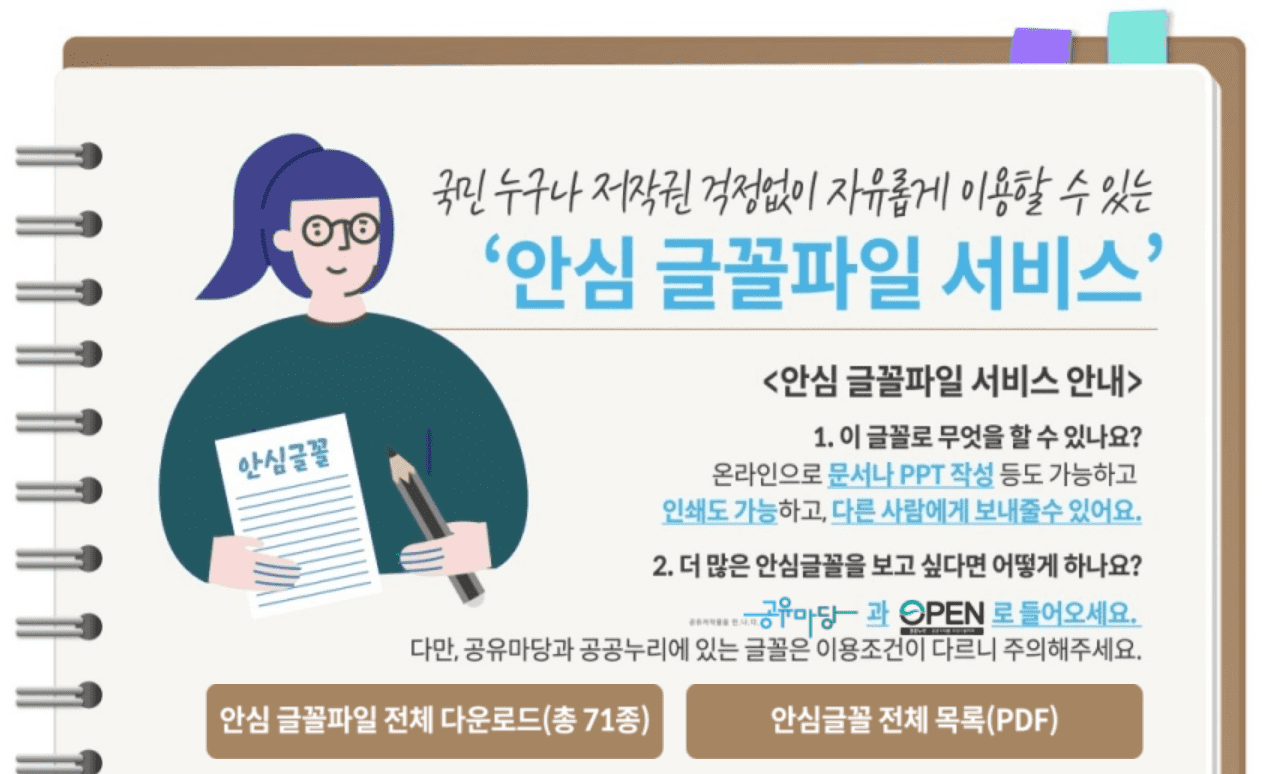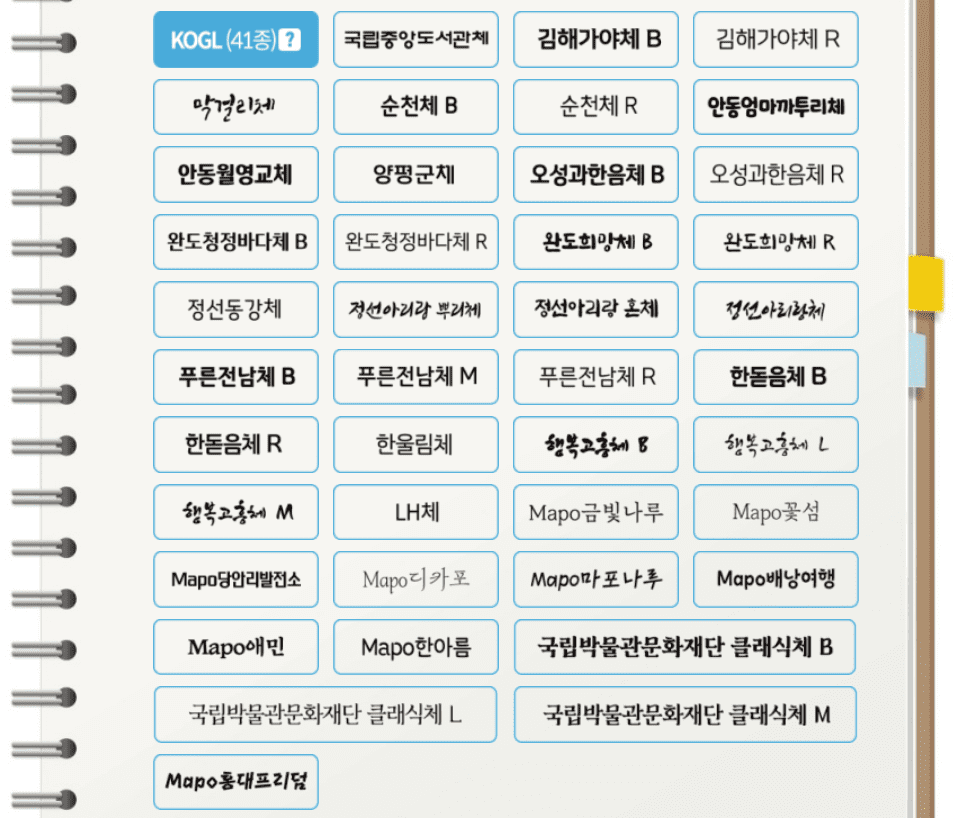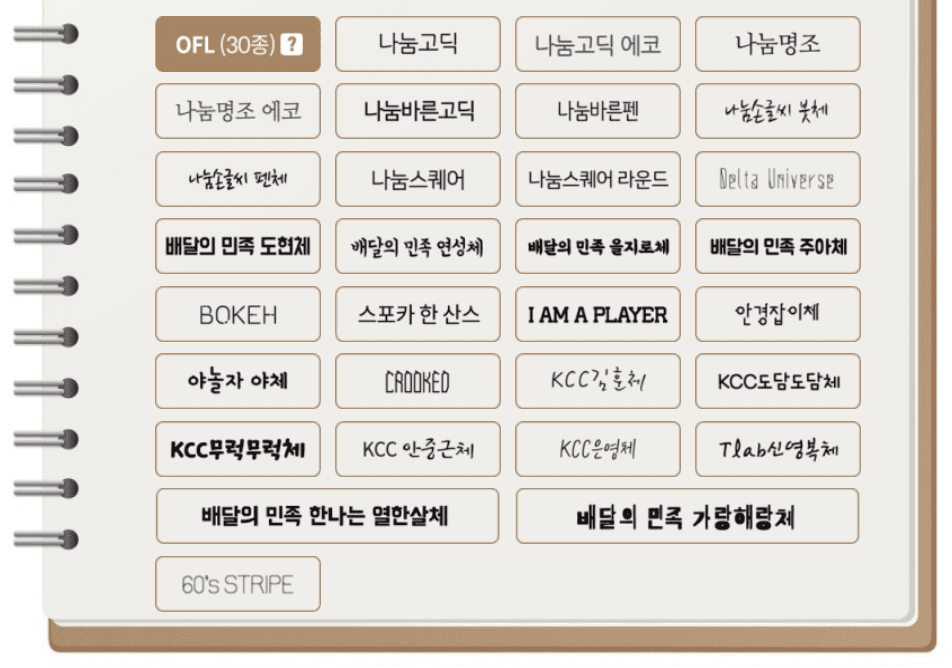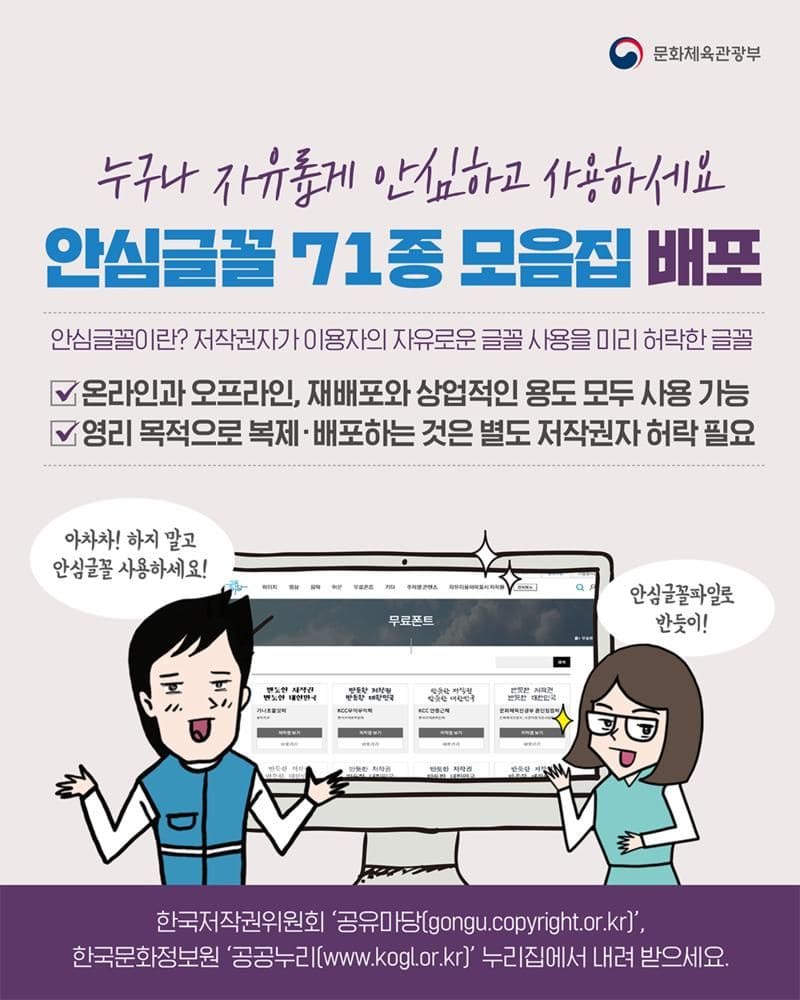
저작권 걱정없는 무료 폰트-안심글꼴(140종)
안심글꼴 71종 모음집이 배포됐어요. (69종 추가됨)
이미지 작업이나 영상편집 할 때 폰트 구하기도 번거롭고, 라이센스를 피해서 개인적 혹은 상업적으로 사용해도 문제없는 것을 찾는 것도 일이죠. 무료의 경우 너무 자주 보다보니 식상하거나 디자인이 만족스럽지 못한 경우도 많이 있었는데요.
이번에 저작권자가 이용자의 자유로운 글꼴 사용을 미리 허락한 글꼴들을 무료로 다운로드받을 수 있게 배포했네요. 그전에도 무료로 풀려 있던 폰트들이 많이 있지만, 이런 식으로 한 군데 사이트에 모아 놓으면 더 이상 폰트 찾아 방황하지 않아도 될 정도예요.
저작권 걱정없는 무료 폰트 안심글꼴 140종
안심글꼴 목록 1
안심글꼴 목록 2
유튜브 자막이든 이미지 작업이든 충분히 활용할 수 있을 만큼 종류가 다양하고 퀄리티 좋은 것도 많이 다운받을 수 있어요. 예전보다 이쁜 글씨체가 많이 늘어난 것 같아요. 필기체 같은 느낌, 붓글씨 같은 캘리그라피 느낌도 나는 폰트들도 있고요.
안심글꼴 샘플
전 개인적으로 배달의민족을 좋아하는데 이번에 나온 것인지 전에 못보던 을지로체가 특히 아주 마음에 들어요. 복고 느낌도 나고 투박하면서 동글동글 귀엽고 눈에 잘 띄고. 을지로체 말고도 다른 배달의민족 시리즈도 추천합니다.
안심글꼴 중에서 자주 쓰게 되는 건 배달의민족 시리즈다. 을지로체 외에도 연성체(부드럽고 둥근 손글씨), 주아체(두껍고 시원한 디자인)가 유튜브 썸네일이나 SNS 카드뉴스에 잘 어울린다. 눈누(noonnu.cc)는 검색 기능이 잘 돼있어서 분위기별로 골라볼 수 있다.
네이버 클로바가 AI 기술로 만든 나눔손글씨 109종입니다. 일반인들의 글을 폰트로 만든 듯 아주 자연스럽고 연령별로 다양해 손글씨 중에 마음에 드는 글씨체를 선택하기 좋습니다.